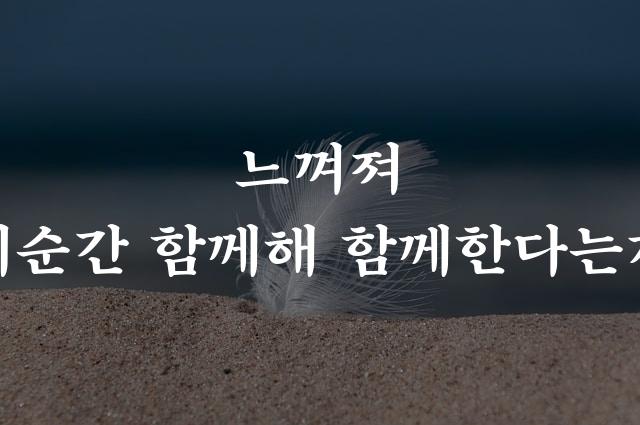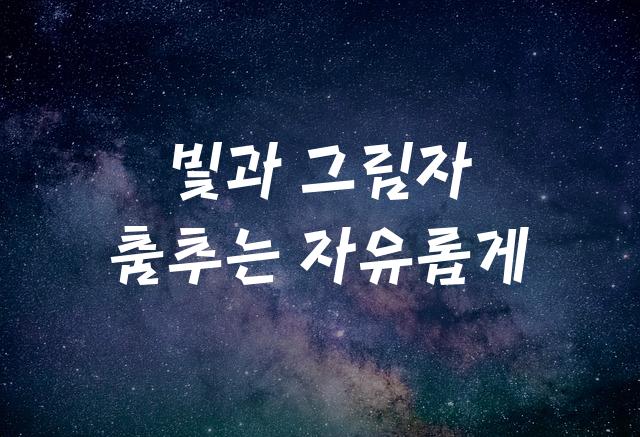
마포마포나루는 마포구에서 제작한 독특하고 각진 손글씨 스타일의 폰트입니다. 이 폰트는 마카를 사용한 듯한 거친 질감과 강렬한 개성이 특징입니다.
마포마포나루은(는)
손글씨, 펜/붓터치, 네모꼴, 감성적인, 단단함 계열의 생김새를 가지고 있으며
브랜딩, 소셜 미디어 등에서 자주 활용되며, 효과적인 메시지 전달에 적합합니다.
이 폰트는 광고/마케팅, 문화/예술 분야에 잘 어울리며,
친근한, 전문적인 느낌을 담고 있는 것이 특징입니다.
이 폰트와 유사한 폰트로는 손글씨 폰트, 블랙잭, 빙그레체 등이 있어요. 함께 비교해 보시면 좋습니다!